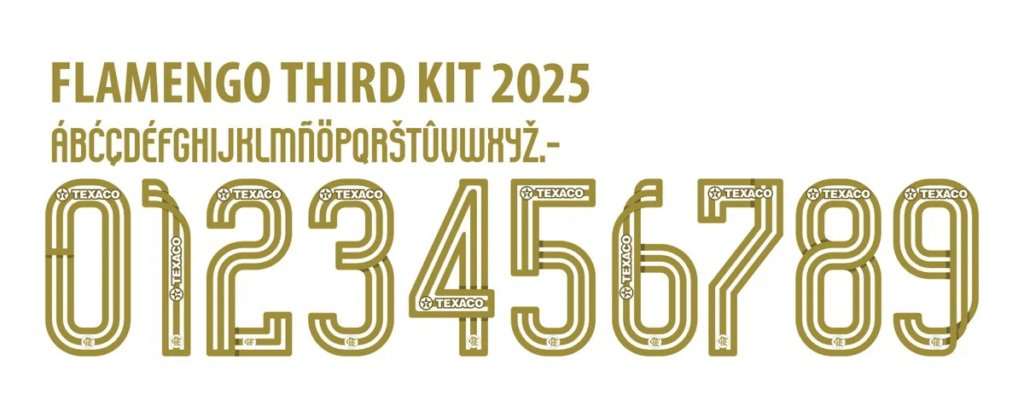
A nação rubro-negra já está de olho no futuro! A Adidas e o Flamengo mais uma vez inovam, e o terceiro uniforme para a temporada 2025 chega com uma identidade visual que promete marcar época. Mais do que um simples uniforme, a nova camisa traz uma tipografia exclusiva, cheia de atitude, que estampa os nomes e números dos craques do Mengão no Brasileirão, Copa do Brasil e Libertadores.
- Uso Ideal: Perfeita para criação de mockups de camisas, artes para redes sociais, banners, estampas personalizadas e qualquer projeto que exija a identidade visual exata do Flamengo na temporada 2025.
Estilo Visual: Modernidade e Impacto
A fonte desenvolvida pela Adidas para o terceiro manto do Flamengo em 2025 é uma verdadeira declaração de modernidade. Ela apresenta traços robustos e angulares, com “cortes” estratégicos que sugerem movimento e dinamismo.
É uma tipografia que abandona o tradicional, trazendo um ar mais tecnológico e agressivo, refletindo a energia vibrante que vem das arquibancadas. A legibilidade é excelente, garantindo que nomes e números se destaquem com clareza e impacto, seja no campo ou em seus designs.